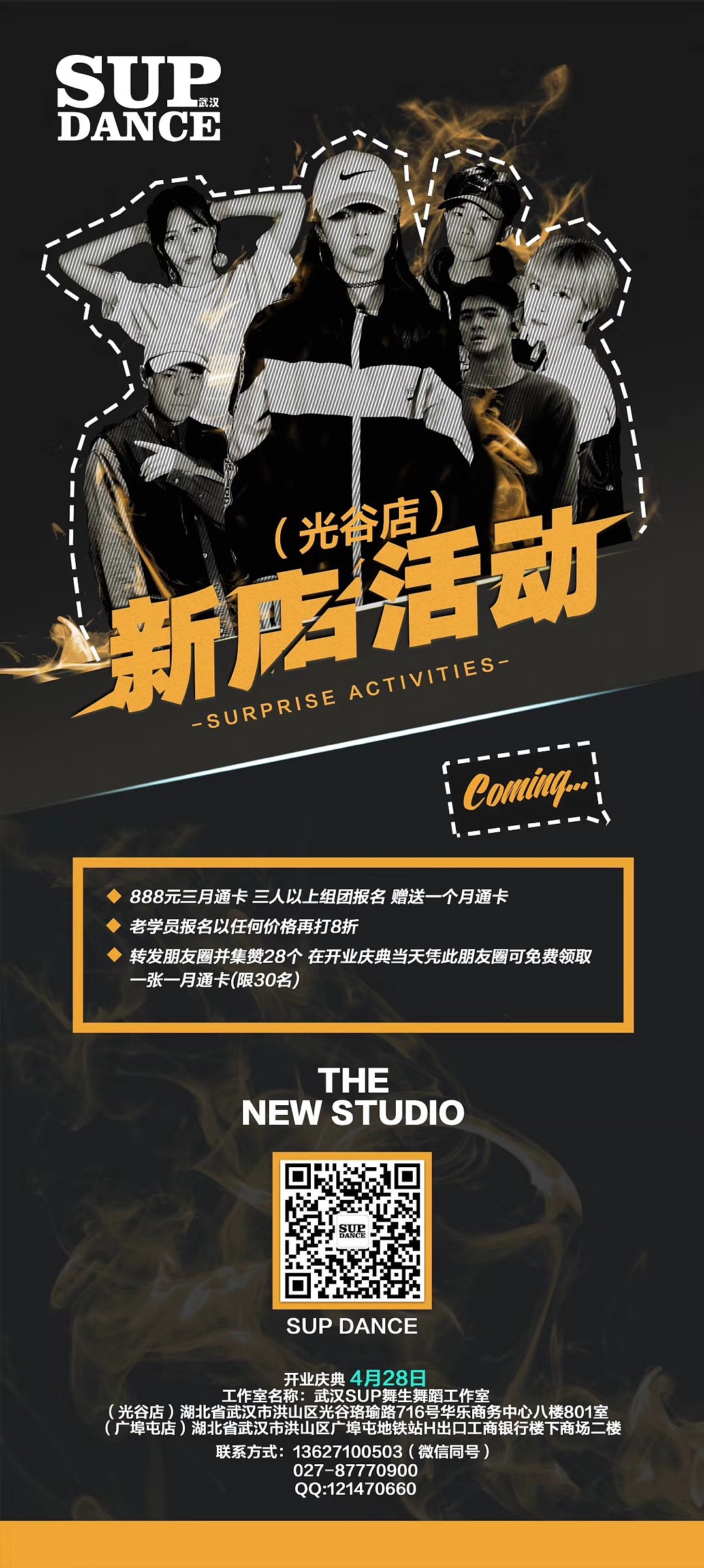
自己创作的那些商业海报
创作的第一张,也是最普通的一张。
第二张开始采用一些特殊的字体,这个形式与配色是段构思的,可能不太符合我的审美  hhhhh 我和他经常互相吐槽 但关系还是那么好
这个是我比较满意的一张,从花瓣网上看了许许多多,这个的字体虽然简单,但破了形之后的锋锐感就凸显出来。这主要是我想的,还加入了网红p图的形式。
这与前一张是一款,但是我喜欢这个颜色,商家也赞同,所以留了一份。